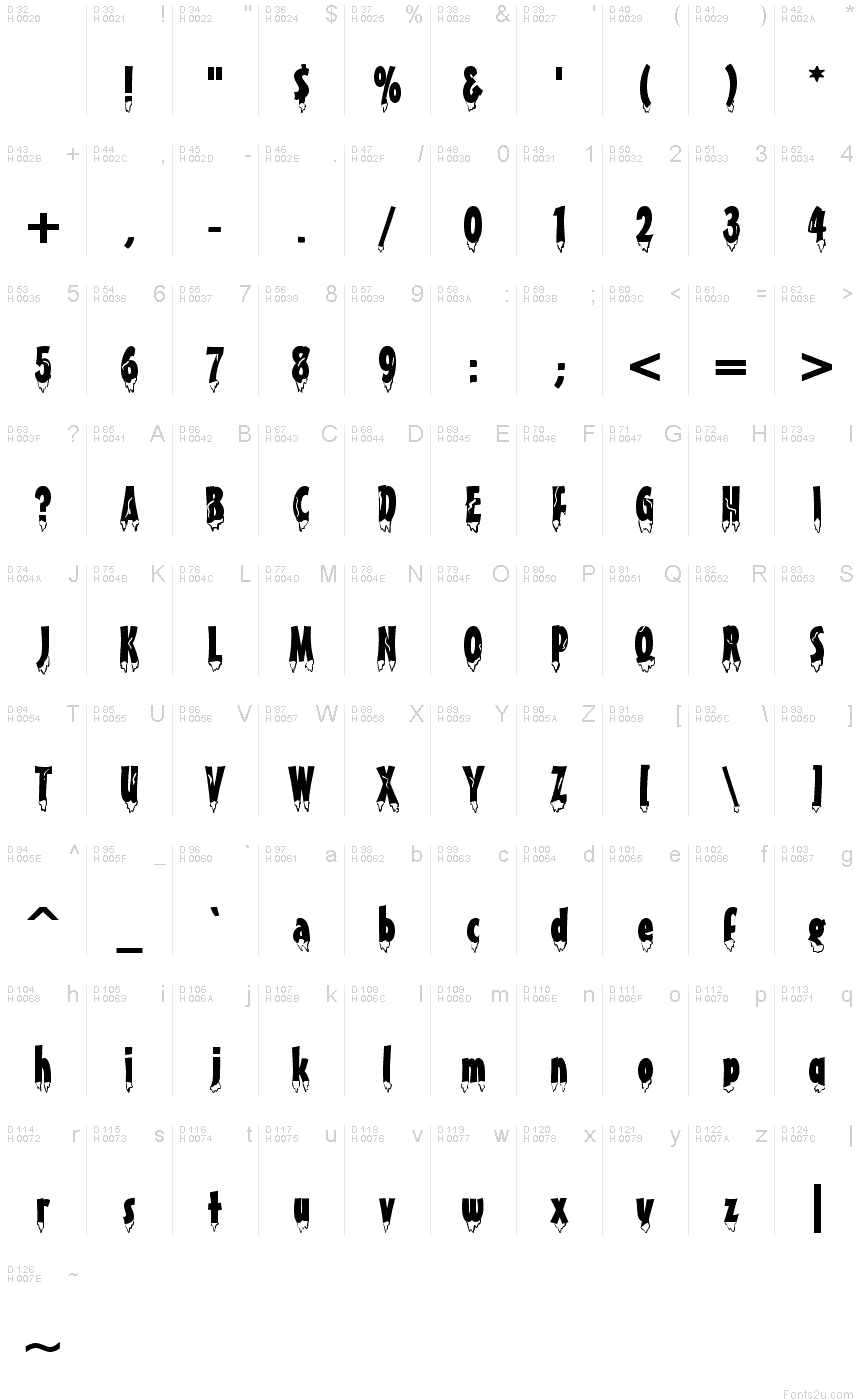
Eiszapfen autorstwa Erstell von J. Modis to darmowy, dekoracyjny krój pisma typu display. Grube, nasycone tuszem znaki zdają się uginać pod ciężarem ostrych, kreskówkowych sopli, nadając każdemu słowu mroźnego, nieco psotnego charakteru. Mocne górne partie liter są czytelne nawet z dystansu, a kapiące kształty u dołu wprowadzają zimowy klimat, unikając przy tym ciężkiej lub ponurej atmosfery.
Dzięki Eiszapfen nadasz zimowy, wyrazisty styl festiwalom, plakatom stacji narciarskich, świątecznym ulotkom, zaproszeniom na śnieżne imprezy, kartkom okolicznościowym czy sezonowym grafikom witrynowym. Ten darmowy font świetnie sprawdza się w dużych rozmiarach, gdzie detale sopli pozostają ostre; w tekście głównym połącz go z prostym krojem bezszeryfowym, aby zachować czytelność i lekkość projektu.